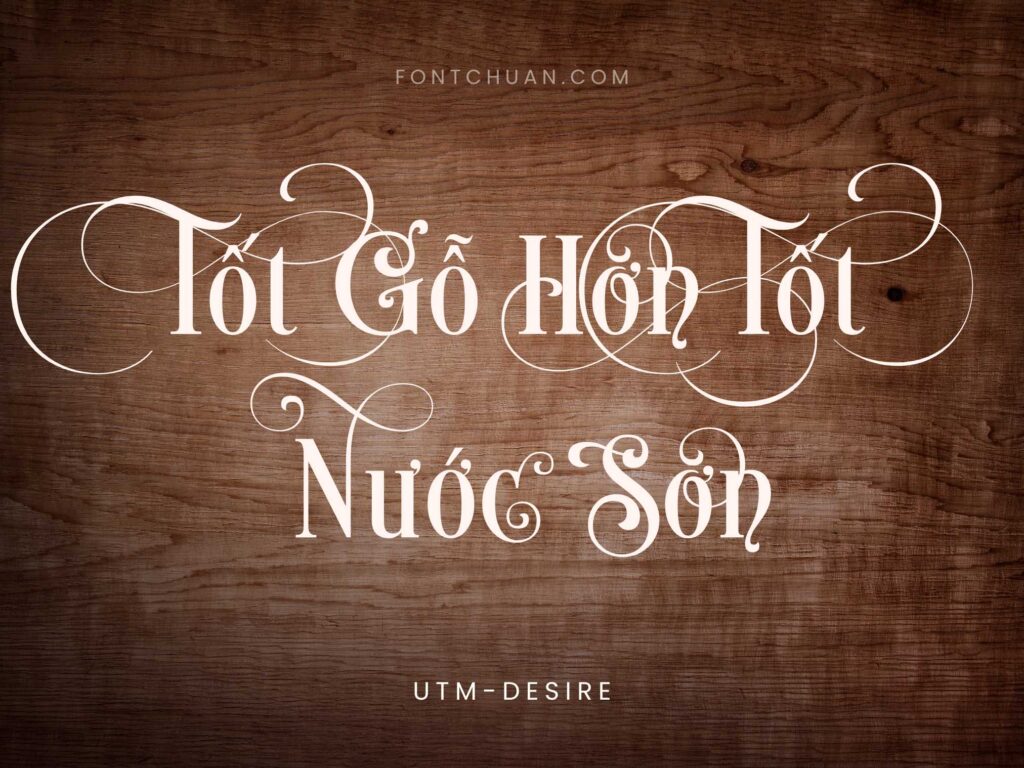
Font UTM Desire Việt Hóa là một kiểu chữ serif trang trí độc đáo, mang phong cách cổ điển nhưng vẫn giữ được nét hiện đại. Font gốc có tên là Desire, được sáng tạo bởi Charles Borges de Oliveira. Với 644 ký tự thay thế, 98 ligatures, 8 flourishes và 6 catchwords, font này cung cấp một bộ tùy chọn phong phú để tạo ra các thiết kế logo, tiêu đề và tiêu đề phụ. Nó phù hợp cho sách, biên tập, bao bì, quảng cáo, thương hiệu và nhiều hơn nữa.
Font này đã được Việt hóa để hỗ trợ đầy đủ tiếng Việt bởi Thiên Minh, ngoài ra còn hỗ trợ hơn 200 ngôn ngữ khác. Thành viên của Font Chuẩn đã sưu tầm và chọn lọc font này nhằm đáp ứng nhu cầu của người dùng trong thiết kế và ứng dụng thực tế. Với đường nét tinh tế và đa dạng, font này phù hợp cho các dự án như thiết kế logo, bìa sách, quảng cáo và nhiều lĩnh vực sáng tạo khác.